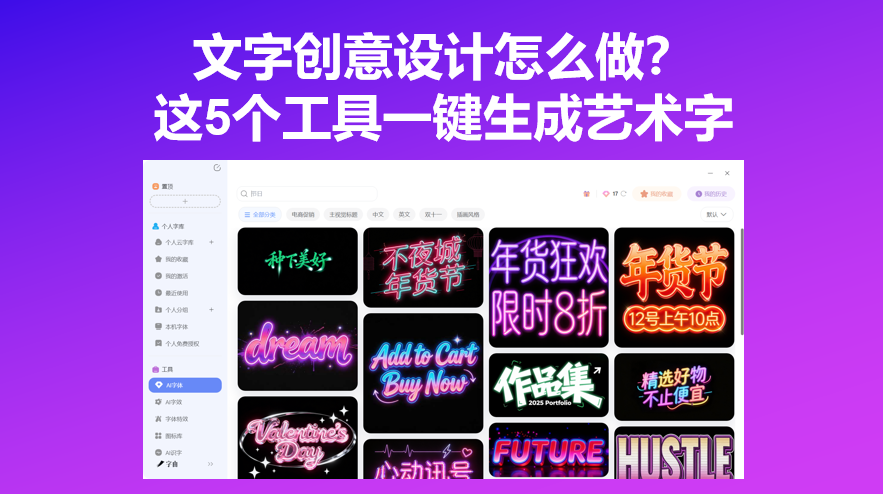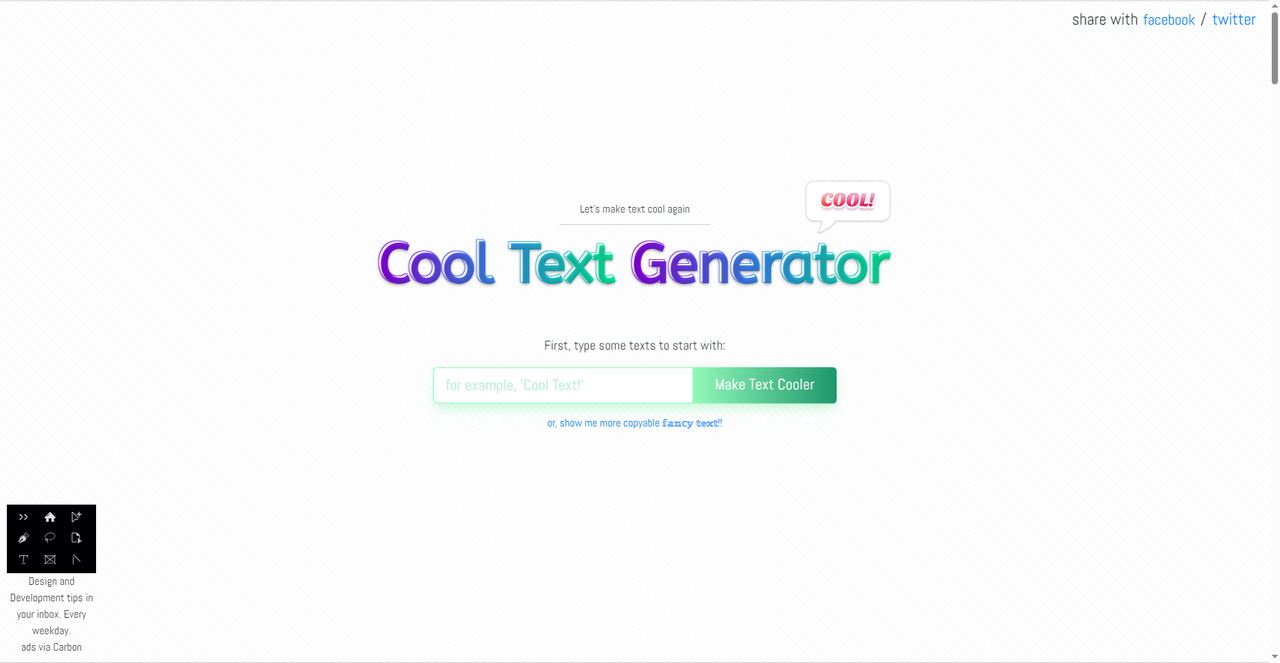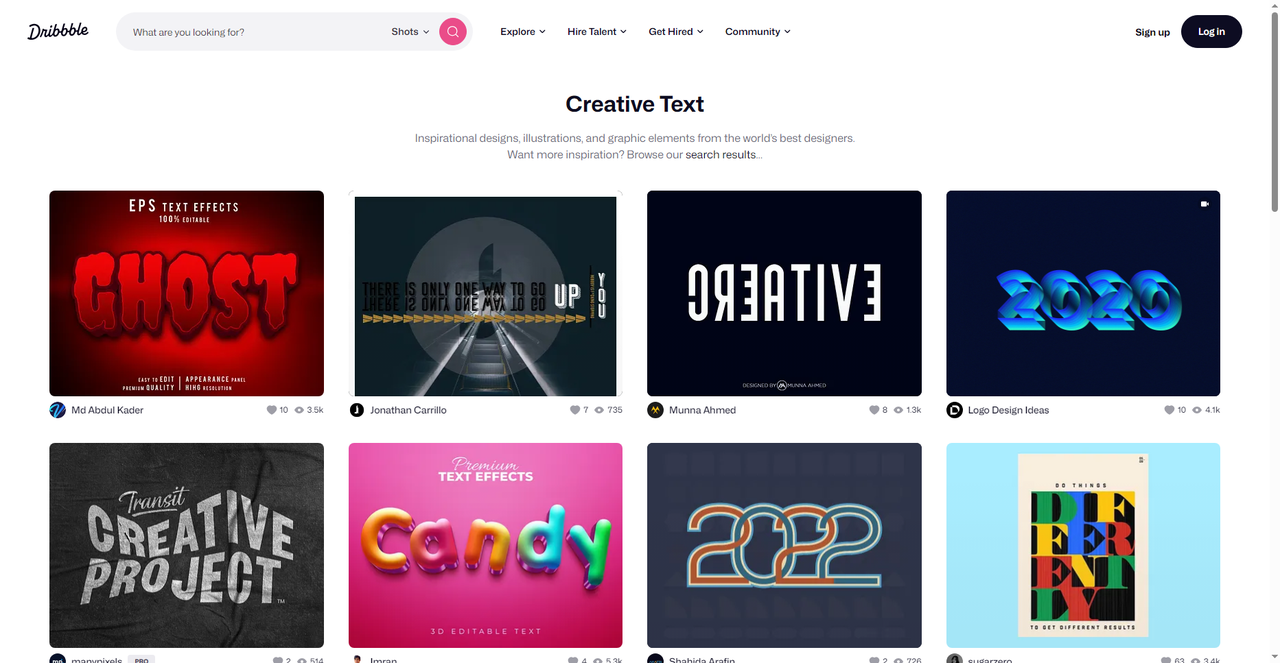
文字创意设计怎么做?这5个工具一键生成艺术字
市面上的创意字数不胜数,但是总有怎么找都不满意的时候,那么这时候大部分人都会想到原创设计,不过原创设计也是需要一定的功底和审美的。相比起自己从零开始设计,不如试试文字创意设计生成工具,只需要选好模板,点击生成即可。今天我整理了5 个一键生成创意文字的工具,从字由的AI字体模板到Cool Text、TextStudio、TextFX和Creative Text 的灵感库,需要的可以收藏。
先来介绍一下字由,字由作为字体库注册用户超过2000万,跟汉仪字库、蒙纳字库等头部厂商都有深度合作,字由在国内字体圈的地位不用多说。它的AI字体功能就在官网“AI工具”里,打开就能看到几百款预制模板,按电商促销、新媒体封面、国潮风、手写书法、科技感等分类排好了。
操作流程是这样的:先筛选场景,比如要做一张奶茶店的菜单海报,在“风格”里选国潮风,翻到喜欢的模板点“生成同款”;然后在右侧输入自己的文案,比如“春日限定 杨枝甘露”,点“立即生成”;等5到8秒,系统就会生成一张艺术字图片,下载 PNG 就能直接用。
如果简洁一点来说,总共就三步:选好模板风格、改成自己的文案、下载保存。对于那些不需要打开 PS 硬调参数的用户来说,基本是零门槛。字由的AI字体每天登录会赠送免费算力,普通用户日常使用不用额外花钱。生成的图片背景透明,适合直接贴到海报、封面、Banner 里。
2、Cool Text Generator
第二个工具叫Cool Text Generator。这是一个在线艺术字生成器,最大的优势就是“轻”——不用注册,不用安装,打开网页就能用。Cool Text 提供了几十种文字特效,包括霓虹灯效果、金属质感、玻璃质感、3D 立体字等。你只需要在输入框里打字,然后从列表里选一个喜欢的特效,系统会立即生成预览图。满意了就可以下载 PNG 格式,直接用在社交媒体封面、视频标题、个人简介等场景。
Cool Text 的特效库更偏“欧美潮流风”——有些是火焰效果、有些是冰霜效果、有些是复古霓虹招牌。如果你需要的是那种视觉冲击力强的标题字,Cool Text 的特效种类可能比字由更丰富。不过它的字体以英文字体为主,中文字体的兼容性一般,更适合做英文内容的创意设计。
值得一提的是,Cool Text 还支持批量生成,输入多行文字可以一次性生成多个版本,方便对比挑选。
3、TextStudio:3D
第三个工具叫TextStudio。如果说字由是“模板多”,Cool Text 是“特效多”,那 TextStudio 就是“3D 强”。它是一个在线 3D 文字特效生成器,支持创建立体感十足的文字效果。打开 TextStudio,输入你的文案,系统会生成几十种预览效果,包括金色质感、霓虹灯、火焰、金属、涂鸦、霓虹、3D 等十几个大类。选中心仪的效果后,可以进入编辑界面进一步调整——字体、颜色、描边、阴影、3D 厚度、光照角度,全都能调。TextStudio 最亮眼的功能是 3D 文字动画。你可以给文字加上旋转、缩放、位移等动态效果,导出为 GIF 或 GLB 3D 模型。这对于做视频片头、动态海报、品牌 LOGO 动画的人来说非常实用。
4、TextFX
第四个工具叫TextFX,一款实验性 AI 工具,专门为文字创作者设计。和前面几个不太一样,TextFX 做的不是“给文字加特效”,而是“给文字加创意”。它提供了一系列 AI 驱动的文字游戏工具——比如输入一个词,它会自动生成押韵的词组;输入一个概念,它会生成比喻和明喻;它还能生成头韵、变位词、拆词组合等。这其实也是一种文字创意设计,只不过设计对象是文字的内容本身,而不是文字的视觉效果。如果你是写文案、写歌词、写诗的人,或者在做品牌 Slogan 时需要一些灵感和新角度,TextFX 的这套工具组合非常有意思。它完全免费,不需要注册,打开网页就能用。不过目前主要支持英文,中文场景的适配度一般。
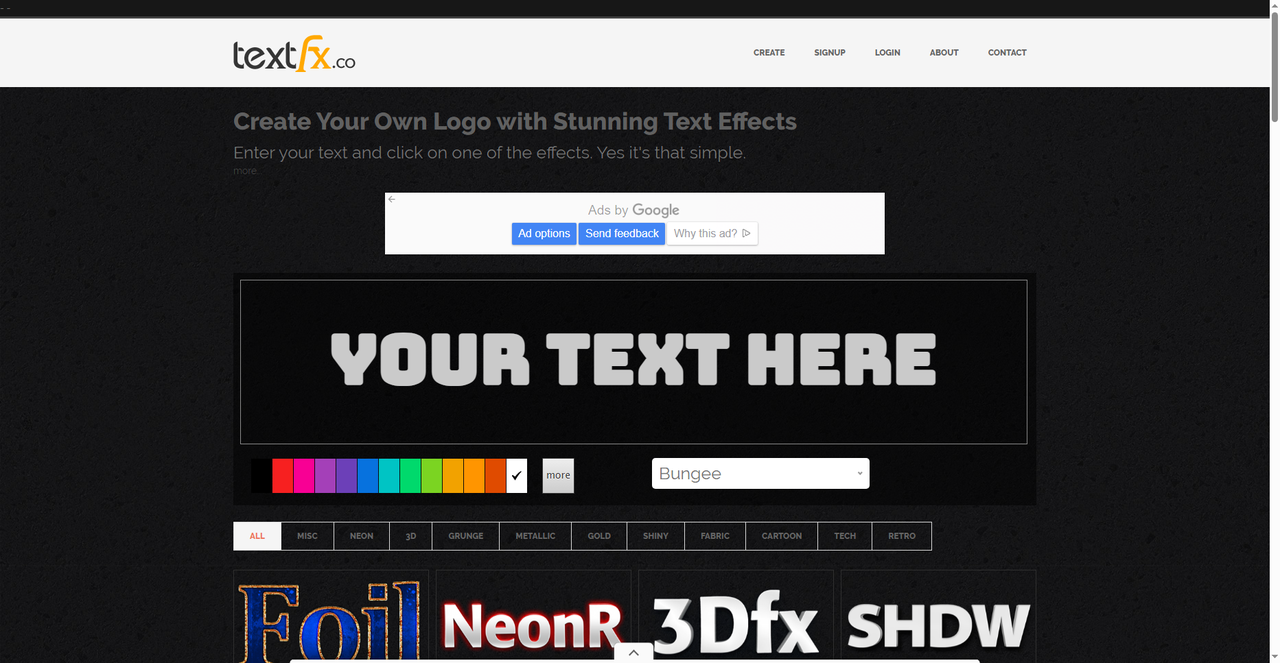
5、Creative Text
最后一个网站叫Creative Text。严格来说,它不是生成器,而是一个设计灵感聚合平台。Creative Text 上汇集了大量来自全球设计师的文字创意作品,包括 3D 文字效果、霓虹灯招牌、金属质感标题、涂鸦字体等。你可以按热门程度或最新发布浏览,看到喜欢的作品可以点击进去查看设计思路、使用的字体和工具。它的价值在于:当你面对一张空白画布不知道从哪下手时,翻一翻 Creative Text 的作品,很快就会找到方向。很多设计师在开始做 Logo 或海报之前,都会先来这里刷一刷找感觉。这也是文字创意设计工作流中不可或缺的一环——先找灵感,再用工具实现。
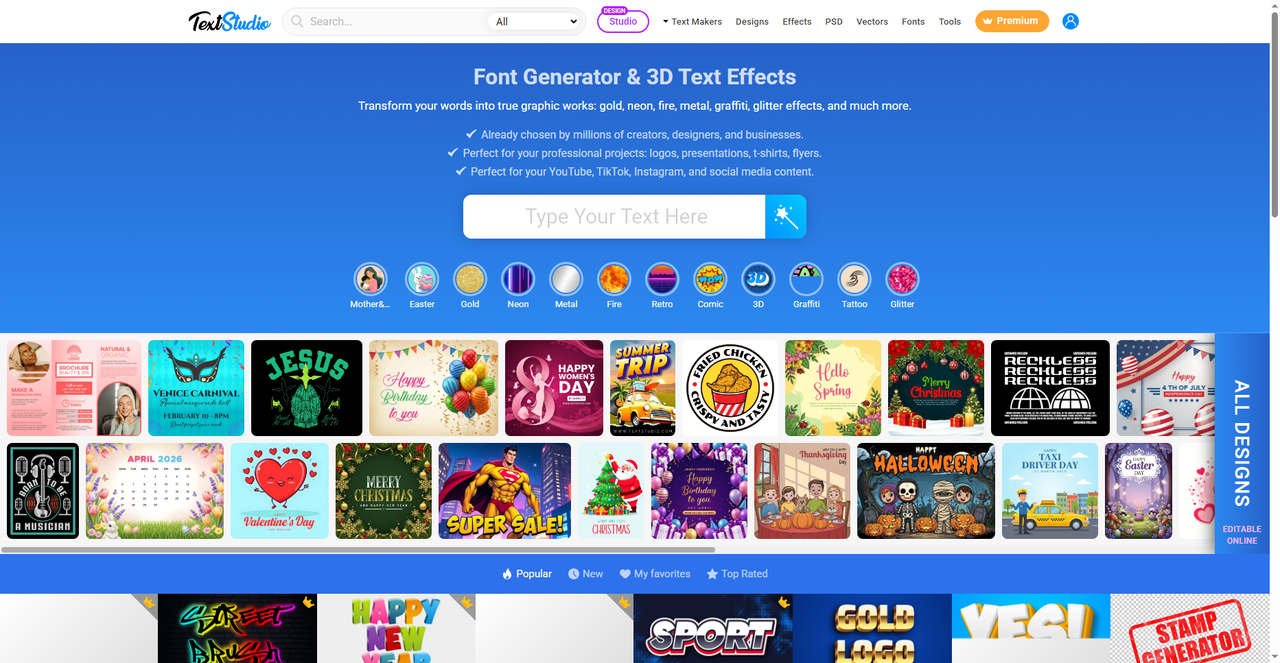
再说回来,这里面我最常用的还是字由,因为中文字体模板比较多,能够适应不同场景的需求,不过做个英文视频封面,可能 Cool Text 的特效更抓眼球;做个 3D LOGO 动画,TextStudio 更专业,这些都各有所长,工具没有高下之分,只有合不合适。只需要记得下次做海报标题的时候,别在 PS 里闷头苦干了,。